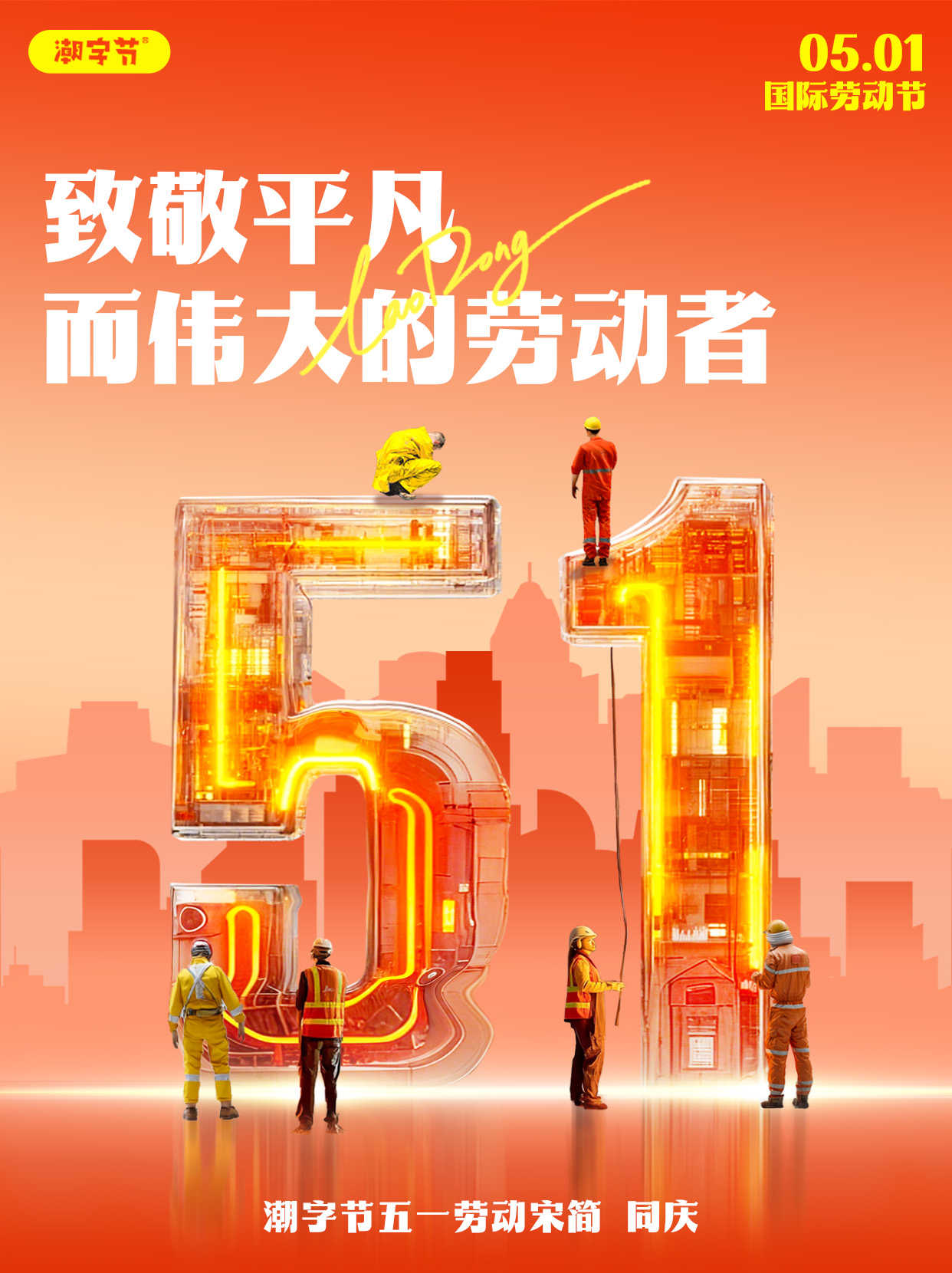
潮字节五一劳动宋简 同庆
Jump-MayDayGB-Celebrate
潮字节五一劳动宋简 同庆是一款充满干劲与斗志的创意宋体。整体字形高大壮硕,高挑的重心如同充滿理想的劳动者一般挺拔有力。笔画设计粗壮质朴,曲线利落硬派,装饰方正简洁,有一种飒爽刚毅、健康有力、乐观大方的美。适用于节日海报宣传、品牌标识、文创设计、新闻标题等应用场景。